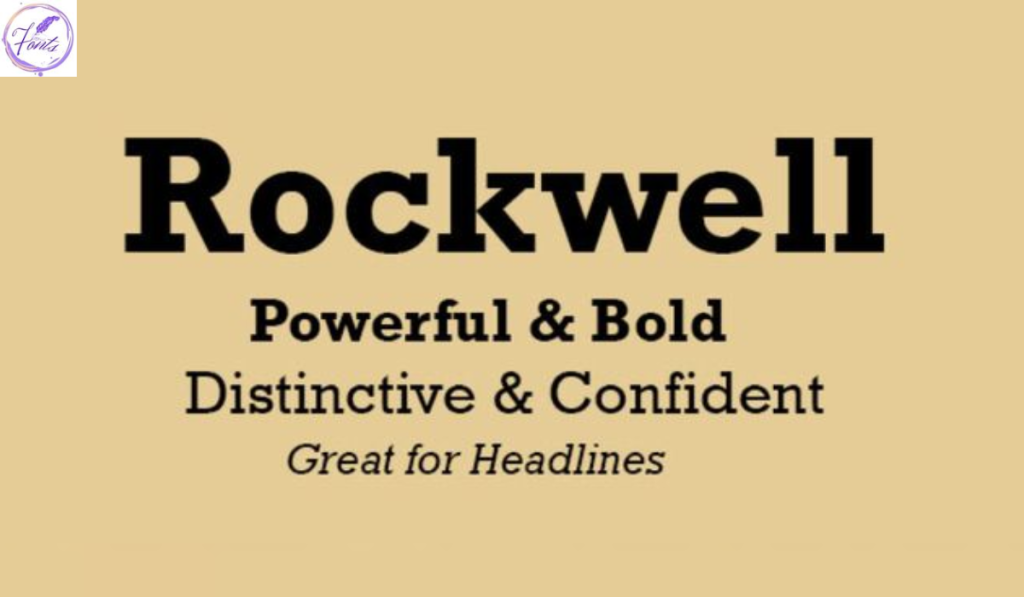
Font Rockwell việt hóa
Tác giả: Frank Hinman Pierpont
Ngày phát hành: 1934
Ngôn ngữ: Tiếng Việt, Tiếng Anh, và nhiều ngôn ngữ khác
Bộ Font: Rockwell
Phân loại: Cá tính, độc đáo
Kiểu chữ: Kiểu chữ có chân
Độ dày: Light, Regular, Bold, Black
Chào mừng bạn đến với bài viết về font rockwell việt hóa! Font rockwell là một trong những font chữ được ưa chuộng nhất hiện nay, đặc biệt trong thiết kế đồ họa và in ấn. Với kiểu dáng thanh lịch, dễ đọc và tính linh hoạt cao, font rockwell đã chinh phục được trái tim của nhiều nhà thiết kế và doanh nghiệp. Trong bài viết này, chúng ta sẽ cùng khám phá những đặc điểm nổi bật của font rockwell và lý do vì sao nó lại trở thành lựa chọn hàng đầu của giới thiết kế.
Đánh giá font rockwell
Font rockwell sở hữu những nét đẹp độc đáo và cuốn hút. Các đường nét mềm mại, bo tròn tạo cảm giác thân thiện và dễ chịu cho người đọc. Đồng thời, font rockwell cũng mang lại sự chuyên nghiệp và sang trọng cho các ấn phẩm. Với bộ font đầy đủ các phông chữ và kiểu in khác nhau, font rockwell có thể đáp ứng mọi nhu cầu thiết kế, từ thiết kế logo, bao bì sản phẩm cho đến thiết kế website và quảng cáo. Nhiều tạp chí nổi tiếng như Forbes, Time, và National Geographic đã tin tưởng sử dụng font rockwell trong các ấn phẩm của mình.